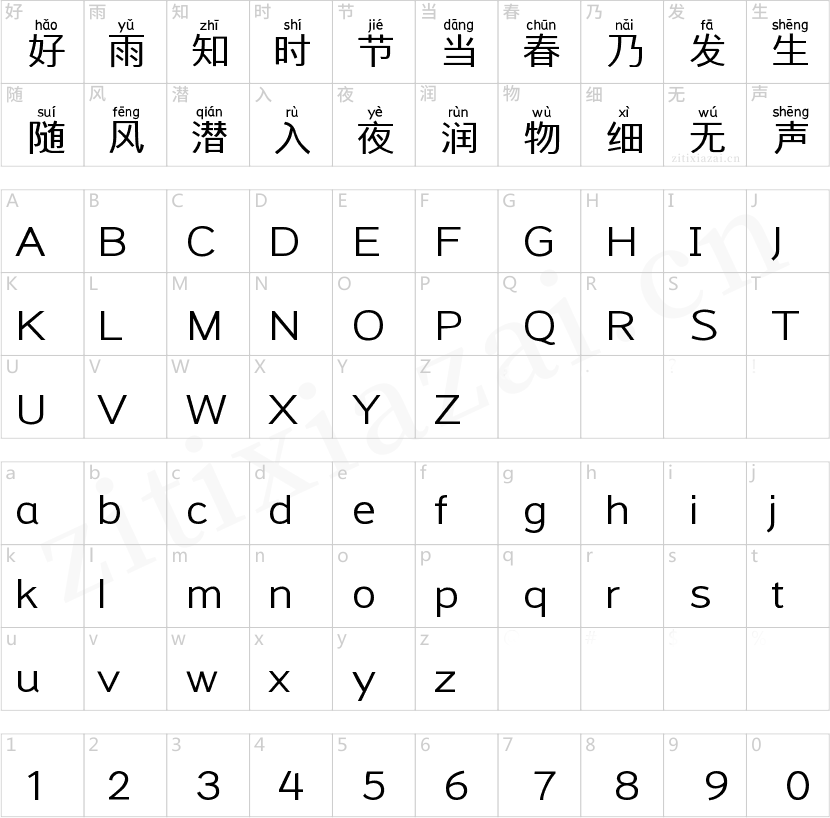
Aa扁黑拼音体
Aa扁黑拼音体,这款字体结构工整、笔画清晰,兼顾美观与易读性,适用于标题、正文、海报、包装、LOGO 等多种场景。字形优雅稳定,风格百搭耐看,适配日常排版与创意设计,让文字呈现更舒适、更具质感。Aa扁黑拼音体一笔一画,皆是细节,以均衡的比例、流畅的线条打造舒适视觉体验,字形端正大气,风格简约现代。无论是商业设计、品牌宣传还是日常排版,都能轻松驾驭,让文字更有格调与力量。Aa扁黑拼音体字体下载。
Aa扁黑拼音体是一款非常具有艺术性的字体,它的设计灵感来源于对古典艺术的研究,同时又融入了现代字体设计的元素。字形优美,笔画粗细变化自然,给人以大气、典雅的感觉。Aa扁黑拼音体是一款既传统又现代的字体,它的设计充满艺术感,美观大方,实用性也非常强。无论是对于设计师还是对于普通读者来说,都是一种非常不错的字体选择。Aa扁黑拼音体适合用于具有艺术感的场合,比如海报、宣传单张、书籍封面等。由于其字形流畅且具有动态感,也适合用于大量的文本排版,如报纸、杂志等。